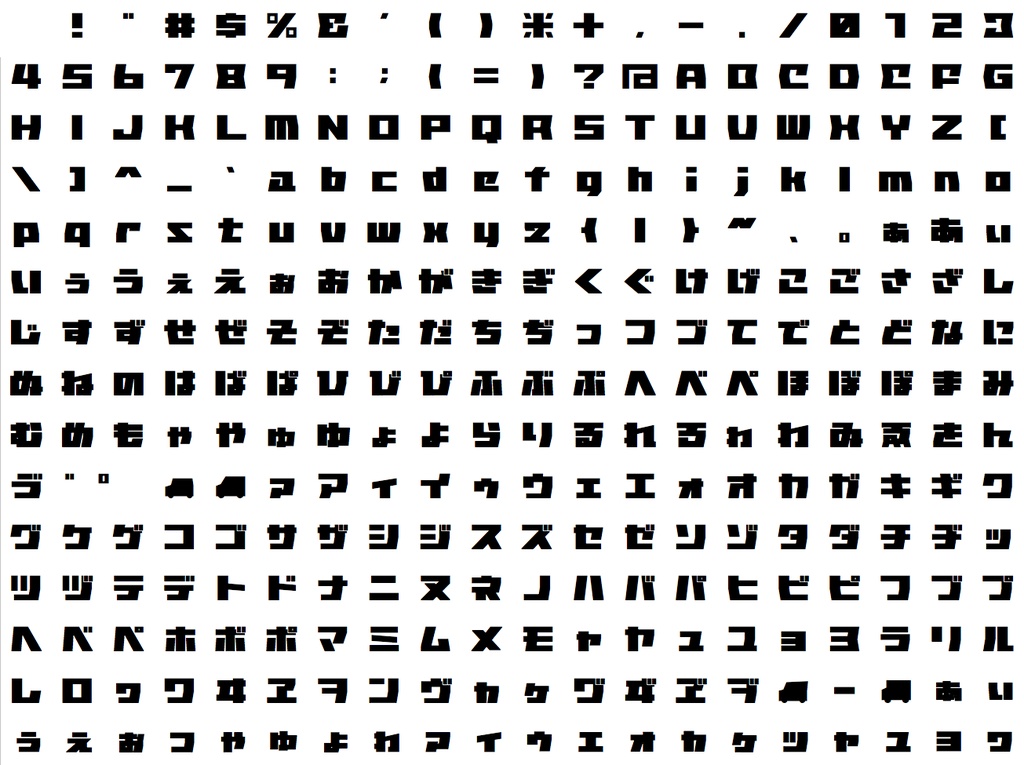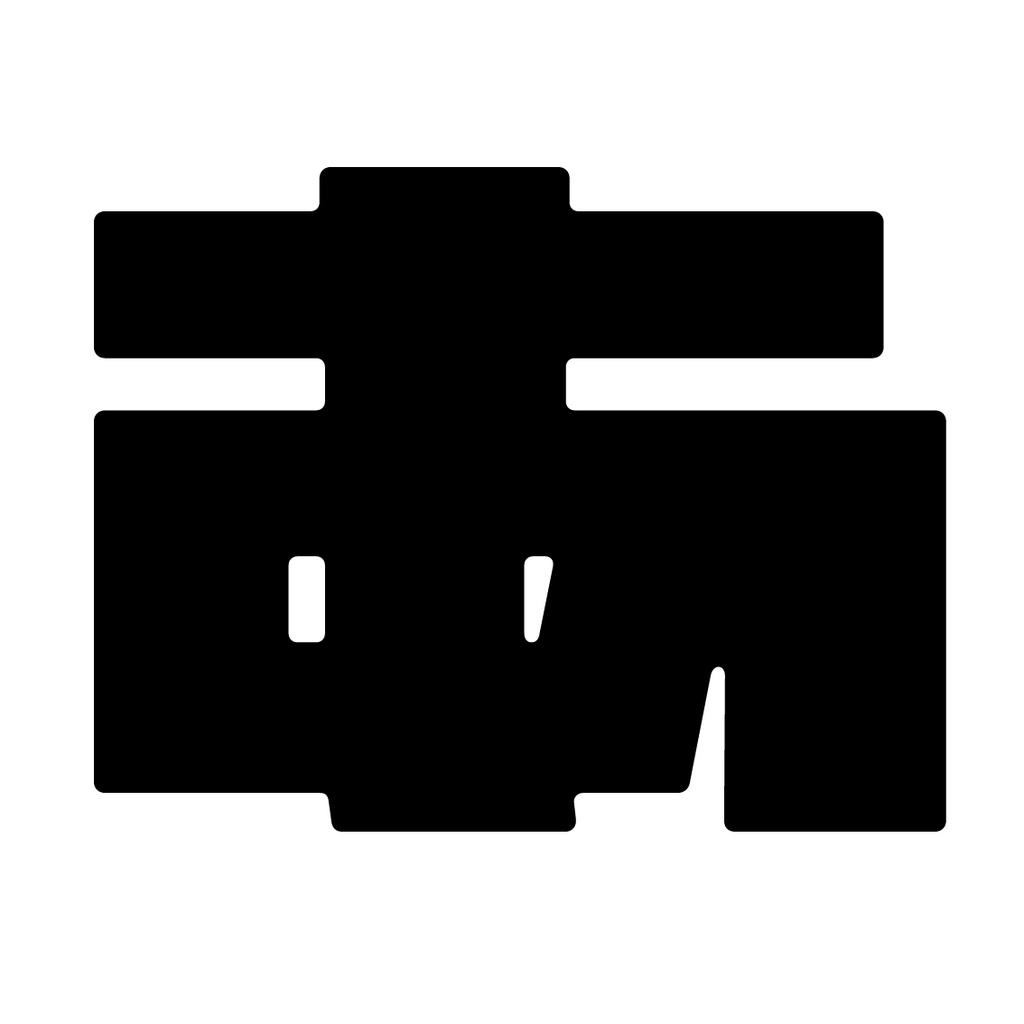
ミニバン2 フォント
ミニバン2フォント かわいくて、かっこいいPOPなデザインのフォント。インパクトのあるロゴにぴったりのフォント。ひらがな、カタカナ、アルファベット、記号のみのフォントになります。 2002年に公開した、フォントのリデザインです。ひらがなが加わり、フォントフォーマットが縦書きも出来るOpenType形式になりました。アルファベットとカタカナもデザインの変更が行われました。 ■動作環境 Mac:システム/OS X対応(10.x)〜最新のOS X Windows:OS/日本語版Windows2000、XP、VISTA、Windows7〜11以降 ・Adobeイラストレーター、フォトショップはもちろんのことWindows用ワード・エクセル等でもご使用になれます。 ■安心して使えるロイヤリティフリーの書体 あらゆる商用・デザイン用途(印刷物・ゲーム・アプリ・映像・動画・ロゴ・同人作品)に使用できる、商用申請の必要のないロイヤリティフリーの書体になります。文字の加工・変形も可能です。ご安心ください。